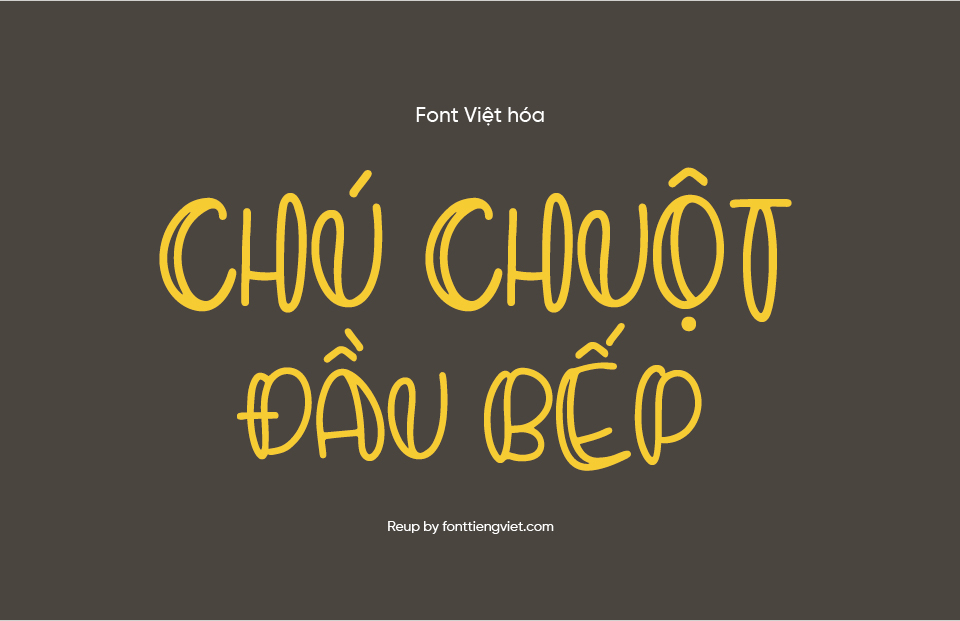
Tải Font Việt hóa MTD Fun Play Day: Lựa chọn Hoàn Hảo cho Thiết kế Giáo dục và Sáng tạo
Trong thế giới thiết kế đồ họa, việc lựa chọn một Font Chữ phù hợp có vai trò cực kỳ quan trọng, đặc biệt là khi đối tượng hướng đến là học sinh, sinh viên hoặc các tài liệu mang tính chất vui nhộn, sáng tạo. Hôm nay, chúng ta sẽ đi sâu vào khám phá một lựa chọn đang rất được yêu thích: Font Việt hóa MTD Fun Play Day. Đây không chỉ là một bộ font đơn thuần mà còn là công cụ giúp các nhà thiết kế giáo dục và các bạn học sinh tạo ra những sản phẩm thị giác cuốn hút, giúp việc học trở nên thú vị và dễ tiếp thu hơn. Phiên bản Việt hóa hoàn chỉnh của MTD Fun Play Day đảm bảo rằng mọi tài liệu tiếng Việt đều hiển thị mượt mà, không bị lỗi dấu, giữ trọn vẹn tinh thần “vui tươi, năng động” của bản gốc.
Giới Thiệu Chung về Font Việt hóa MTD Fun Play Day và Đặc Điểm Nổi Bật
MTD Fun Play Day là một kiểu font chữ viết tay (handwritten font) mang phong cách trẻ trung, hồn nhiên. Thiết kế của nó mô phỏng nét chữ tự nhiên, có chút ngẫu hứng, gợi lên cảm giác thoải mái và thân thiện. Chính nhờ sự độc đáo này, font MTD Fun Play Day thường được sử dụng trong các ấn phẩm dành cho lứa tuổi mầm non, tiểu học, các bài giảng điện tử (e-learning) hoặc các thiệp mời mang tính cá nhân cao. Đặc điểm “Fun Play Day” thể hiện rõ qua sự biến hóa nhẹ nhàng của các ký tự, tạo nên một tổng thể hài hòa và không gây nhàm chán cho người đọc. Sự kết hợp giữa tính nghệ thuật và tính ứng dụng cao giúp font này trở thành một tài sản giá trị cho các dự án liên quan đến sự kiện trường học, kỳ thi tốt nghiệp, hay các hoạt động ngoại khóa dành cho học sinh trung học.
Tại Sao Font MTD Fun Play Day Lại Được Ưa Chuộng Trong Lĩnh Vực Giáo Dục?
Đối với các giáo viên và chuyên gia phát triển nội dung học thuật, việc giữ chân sự tập trung của học sinh, đặc biệt là học sinh trung học và lứa tuổi nhỏ hơn, là một thách thức lớn. Các tài liệu học tập thường khô khan, nhưng khi được “khoác lên mình” những bộ font sống động như MTD Fun Play Day, chúng lập tức trở nên hấp dẫn hơn. Font này giúp làm mềm hóa những thông tin cứng nhắc, biến các slide thuyết trình hoặc tài liệu ôn thi tốt nghiệp trở nên dễ tiếp cận hơn. Sự rõ ràng, dễ đọc nhưng vẫn đảm bảo tính thẩm mỹ cao là điểm cộng tuyệt đối cho font chữ này trong môi trường học đường. Nó hỗ trợ đắc lực cho việc tạo ra các flashcard, bảng tóm tắt kiến thức một cách trực quan.
Ngoài ra, MTD Fun Play Day còn là công cụ tuyệt vời cho các dự án sáng tạo của chính học sinh. Trong các môn học yêu cầu làm báo tường, thiết kế poster cho hoạt động ngoại khóa, hay làm video kỷ yếu cuối cấp, việc sử dụng một font chữ độc đáo như MTD Fun Play Day giúp bài làm của các em nổi bật hơn, thể hiện được cá tính và sự đầu tư nghiêm túc vào mặt hình thức. Đây là một yếu tố quan trọng giúp nâng cao tinh thần học tập và kích thích sự sáng tạo trong cộng đồng học sinh, góp phần vào việc hoàn thành tốt các kỳ thi quan trọng.
Ứng Dụng Sáng Tạo Thực Tế Của Font MTD Fun Play Day
Phạm vi ứng dụng của MTD Fun Play Day không chỉ dừng lại ở trường học. Font chữ này còn được các nhà thiết kế đồ họa chuyên nghiệp sử dụng rộng rãi trong các lĩnh vực thương mại như thiết kế bao bì sản phẩm, logo thương hiệu hướng đến đối tượng trẻ em, hay các ấn phẩm quảng cáo mang tính chất thân thiện, không trang trọng. Sự kết hợp giữa tính chuyên nghiệp trong thiết kế ký tự và vẻ ngoài tinh nghịch khiến nó trở thành một công cụ đa năng. Nó hoàn toàn có thể được dùng để tạo ra các tiêu đề độc đáo cho video hướng dẫn học tập hoặc các meme giáo dục (educational memes) nhằm tăng tính tương tác trên các nền tảng số. Đối với các dự án cá nhân, đây cũng là lựa chọn tuyệt vời cho nhật ký, scrapbook hay thiệp chúc mừng.
Lợi Ích Khi Sử Dụng Phiên Bản Font Việt hóa MTD Fun Play Day Cho Mọi Dự Án
Nhiều font chữ nước ngoài khi được sử dụng tại Việt Nam thường gặp vấn đề về hiển thị dấu, gây mất thẩm mỹ và khó đọc. Phiên bản Font Việt hóa MTD Fun Play Day đã giải quyết triệt để vấn đề này, đảm bảo rằng mọi văn bản tiếng Việt đều được trình bày một cách hoàn hảo. Điều này đặc biệt quan trọng khi soạn thảo các đề thi tốt nghiệp, các tài liệu hướng dẫn học tập có nội dung phong phú và yêu cầu tính chính xác cao. Việc sử dụng font chuẩn Việt hóa không chỉ thể hiện sự chuyên nghiệp mà còn tôn trọng ngôn ngữ và văn hóa Việt Nam. Đây là lý do khiến phiên bản Việt hóa luôn là lựa chọn hàng đầu cho các dự án thiết kế và in ấn tại Việt Nam, từ cấp độ cá nhân cho đến các tổ chức giáo dục lớn, giúp truyền tải thông điệp một cách rõ ràng và sinh động nhất.
Tóm lại, Font Việt hóa MTD Fun Play Day xứng đáng là một công cụ không thể thiếu trong bộ sưu tập của bất kỳ ai làm việc trong lĩnh vực giáo dục, thiết kế sáng tạo, hoặc đơn giản là muốn thêm chút vui tươi vào văn bản của mình. Với phong cách trẻ trung, dễ thương và khả năng hiển thị tiếng Việt hoàn hảo, font chữ này sẽ mang lại luồng gió mới cho các tài liệu học tập, các dự án cá nhân, hay các ấn phẩm quảng cáo. Đừng ngần ngại tải về và trải nghiệm sự khác biệt mà bộ Font Chữ độc đáo này mang lại. Hãy bắt đầu hành trình sáng tạo của bạn ngay hôm nay với MTD Fun Play Day!